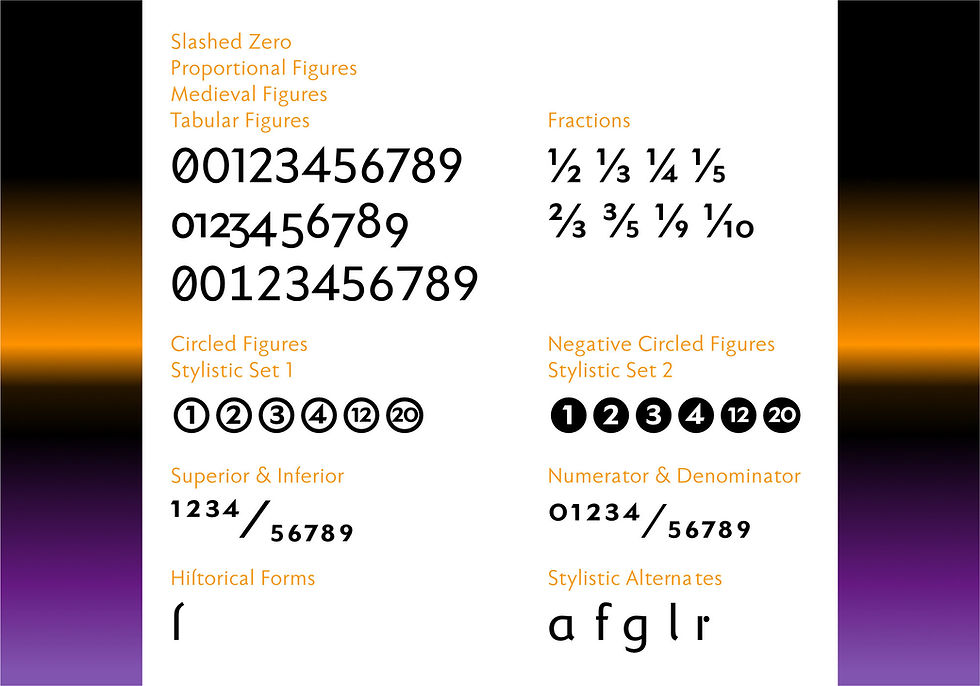
Die klassisch-moderne Serifenlose mit zwei Gesichtern
Zwei Schriften vereint in einer: dank alternativer Buchstabenformen erhält diese Schrift ein zweites Erscheinungsbild.
Die Faber Sans ist eine Serifenlose im Stil der klassisch-modernen Schriftschöpfungen des frühen 20. Jahrhunderts – die Futura von Paul Renner und die Gill Sans standen Pate.
So entstand eine Schrift mit angenehm rhythmischen Proportionen, die ausgesprochen angenehm zu lesen ist, gerade auch in größeren Textmengen, aber auch unter den typografisch widrigen Bedingungen am Bildschirm ist sie angenehm lesefreundlich.
Ein prägnanter Buchstabe ist das f, dessen Oberlänge verkürzt ist und ohne den sonst gewohnten in Leserichtung ausgreifenden Bogen auskommt.
Das bestimmende Element im Schriftbild sind die breiten runden Formen von b c d e o p q und C D G O Q, bei Verwendung der alternativen Form mit ihrem ebenfalls runden a und g wird dieses formale Merkmal noch betont.
Den Kontrast zu den weichen Rundformen bilden die Spitzen bei allen vom Dreieck abgeleiteten Buchstaben: v w z, und besonders die Versalien A M N V W Z.
Eine »zweite« Schrift mit ganz eigenem Charakter entsteht, wenn man für die Buchstaben a f g l u r die Alternativformen aktiviert, die nach dem Vorbild der spätantiken beziehungsweise frühmittelalterlichen Unzialschriften gestaltet wurden. Das r erhält in der Alternativform einen verspielten Punkt.
Anders als bei vielen Serifenlosen gibt es die »Faber Sans« mit einer „echten“ Kursiven. Sie ist runder, die Strichführung ist flüssiger als bei der aufrechten. Einige kursive Buchstaben haben eine gänzlich eigene Gestalt, die deutlich von der Handschrift herrührt, besonders sichtbar bei a und g.
Mehrere OpenType-Features sind in der Schrift enthalten, die nach Bedarf an- und abgeschaltet werden können:
- Alternative Buchstabenformen:
ersetzt die Buchstaben a, f, g, l, r jeweils durch die alternative Variante, auch in den Ligaturen.
- Ligaturen:
ersetzt die Buchstabenfolgen fi, fl, ff, ffi, ffl, ft, tt, Th durch die jeweilige Buchstabenverbindung.
- Bedingte Ligaturen:
ersetzt die Buchstabenpaare ch, ck, mmdurch die jeweilige Buchstabenverbindung und SS durch Versal-ß.
- Tabellenziffern:
ersetzt die normalen Ziffern durch Tabellenziffern mit identischer Zeichenbreite.
- Mediävalziffern:
ersetzt die normalen Ziffern durch Ziffern, die wie die Kleinbuchstaben Ober- und Unterlängen haben.
- Brüche:
ersetzt die Zeichenkombinationen 1/2, 1/3, 1/4 usw. durch die entsprechenden Brüche.
- Null mit Schrägstrich:
ersetzt die normale »offene« 0 durch die Version mit Schrägstrich.
- Echte Kapitälchen:
ersetzt die Kleinbuchstaben durch Großbuchstaben in der optischen Höhe der Minuskeln.
- Historische Buchstabenformen:
ersetzt s durch „langes s“.
- Formatsatz 1:
ersetzt die normalen Ziffern von 1 bis 20 durch Ziffern im Kreis.
- Formatsatz 2:
ersetzt die normalen Ziffern von 1 bis 20 durch negative Ziffern im Kreis.
- Formatsatz 3:
ersetzt die »zweistöckige« Form von a durch die »runde« Variante.
- Formatsatz 4:
ersetzt die »zweistöckige« Form von g durch die »runde« Variante.
- Formatsatz 5:
ersetzt die »steile« Form von f durch die »ausladendere« Variante.
- Formatsatz 6:
ersetzt die »gerade« Form von l durch die Variante »mit Fuss«.
- Formatsatz 7:
ersetzt die »normale« Form von r durch die verspieltere Variante mit Punkt.
- Formatsatz 6:
ersetzt das u mit Abstrich durch die symmetrische runde Form.